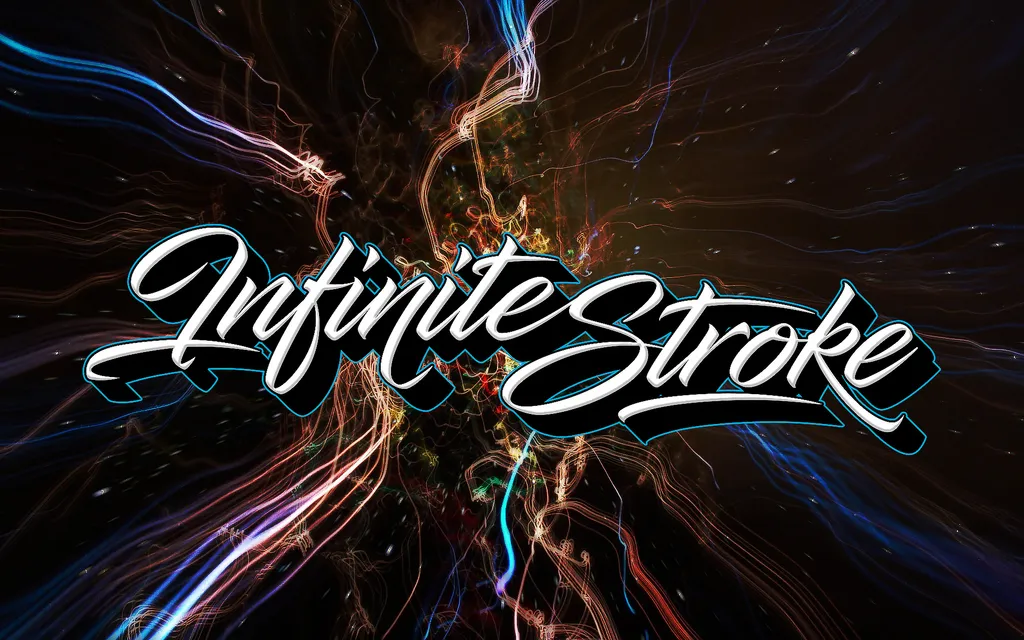
Infinite Stroke Font Family – Fonte Grátis
Infinite Stroke Font Family
Aqui está uma breve descrição para a página de download do famoso família de fóruns “Infinite Stroke” criada pelo designer Youssef Habchi: A Infinite Stroke é uma fonte chamativa que captura os gestos naturais e fluidos da escrita áurea. Esta família de fóruns oferece um vasto leque de opções, desde linhas suaves e expressivas até traços rúnicos e intricados. Sujeitada a um design elegante, ela se destaca em projetos que requerem uma linha fluida e poderosa. Ideal para designers gráficos aficionados e profissionais, esta fonte permite criar escritura chinesa autêntica, letras de livros antigos ou qualquer outro projeto que exige estilo único. Como parte da famosa coleção do designer Youssef Habchi, a Infinite Stroke se torna um recurso indispensável para qualquer editor de texto digital.
Designer: Youssef Habchi